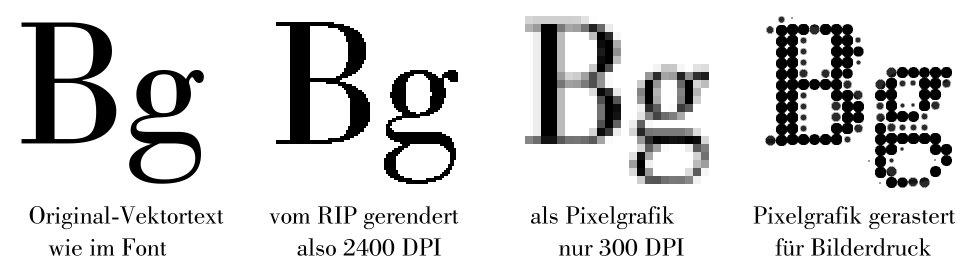
Um das Layout zu bearbeiten benutzen  Gimp (open Source)
Ich möchte da noch einmal dran erinnern. Wenn hier wirklich mit Texten gearbeitet werden soll, ist ein Pixel-Grafikprogramm die denkbar schlechteste Wahl. Textfunktionen von Gimp dienen ausschließlich dazu, in ein Foto mal ein paar Worte einzufügen, aber nicht, um damit ein ganzes Büchlein zu setzen.
Wenn es dann  wirklich ein OpenSource-Progamm sein soll, würde ich mir mal Scribus näher ansehen. Zwar noch immer meilenweit von Profrssionell entfernt, aber immerhin bleiben da Texte auch editierbare Texte, und eben nicht "Bilder von Texten" die man bei einem Schreibfehler komplett neu machen muss - zusammen mit dem Bild in das die dann eingebaut sind.
Notfalls lässt sich sogar Open/Libreoffice noch besser als Satzprogramm missbrauchen.
Wenn hier wirklich mit Texten gearbeitet werden soll, ist ein Pixel-Grafikprogramm die denkbar schlechteste Wahl. Textfunktionen von Gimp dienen ausschließlich dazu, in ein Foto mal ein paar Worte einzufügen, aber nicht, um damit ein ganzes Büchlein zu setzen.
Zum Vergleich: Es käme ja auch wohl niemand auf die Idee, einen Geschäftsbrief mit Wasserfarben und Pinsel zu malen, selbst wenn er keinen Computer hätte. Dann würde man wohl eher noch eine altmodische Schreibmaschine oder, wenn eine solche auch nicht zur Verfügung steht, einen Kugelschreiber benutzen.
… oder jemandem, der über entsprechende Gerätschaften verfügt, sagen: »Schreib mal bitte einen Brief für mich!«.
Ich will mal versuchen, das mit möglichst wenig Fachchinesisch zu erklären.
Es gibt 2 wesentliche Möglichkeiten, Grafiken im Computer zu speichern: Pixel und Vektoren.
Bei Pixeln - so wie sie Gimp verwendet - erzeugst du quasi ein Mosaik aus dem Bild, mit quadratischen Flächen, die jeweils eine bestimmte Farbe haben. Im Prinzip so ähnlich, wie diese "ministeck" Mosaik-Spiele (das waren ja im Grunde die ersten wirklich digitalen (von Digitus, dem Finger) Bildbearbeitungen)
Bei Vektoren dagegen wird nicht die Flache die mit Farbe gefüllt ist, beschrieben, sondern deren Außenkontur über mathematische Formeln, die abschnittsweise die Kurven beschreiben. Das innere dieses Vektor-Objekts kann dann mit einer Farbe gefüllt werden.
Computerschriften (Typ1, TrueType. OpenType sind im Wesentlichen eine Sammlung dieser Vektorgrafiken, ergänzt mit Anweisungen, wie diese dann als Text hintereinander zu reihen sind. Der Vorteil Vektorgrafiken kann man völlig frei beliebig vergrößern, ohne dass diese Mosaiksteinchen sichtbar werden.
Wenn du jetzt dein Bild drucken lassen möchtest, wird ja empfohlen, dass Pixelbilder hier eine Auflösung (bezogen auf die Druckgröße!) von 300 dpi haben sollen also in jeder Richtung 300 Pixel auf einen Zoll Druckbreite oder -Höhe, also auf 25,4mm.
Das bedeutet aber, das so ein Pixel dann knapp 1/10 mm hoch und breit ist.
Das geht dann für den Bildeindruck gut, weil bei Fotos und Zeichnungen, die gemalt sind die benachbarten Pixel sich zumeist nur wenig im Farbton und der Helligkeit unterscheiden.
Druckt man aber so einen Text, werden die Buchstaben eben auch auf diese 1/10 mm verpixelt, so dass im Falle, das die Vektor-Außenkontur beispielsweise genau auf der Hälfte so eines Pixels liegt, dieses komplett (bei schwarzer Schrift) in mittlerem Grau erscheint, und eine dünne Linie des Buchstabens, z.B. eine Serife oder eine Haarlinie färbt dann das Pixel vielleicht nur Hellgrau.
Da aber im Offset-Druck die Druckmaschine eben entweder nur komplett Farbe oder eben keine Farbe aufs Papier drucken kann, müssen Halbtöne dann auch noch gerastert werden.
Hat man aber ein Dokument, indem der Text auch tatsächlich noch Text ist, und zum ausgeben dann der Vektor-Font hinterlegt ist, wird der so genannte "Raster Image Prozessor" der Druckmaschine den Text auch in Pixel überführen, die dann auf die Druckplatte belichtet werden. Dies geschieht dann aber mit einer wesentlich höheren Auflösung mit Pixeln, die dann etwa nur noch 1/100 mm groß sind, und dann auch nicht in Halbtöne umgerechnet werden müssen. Hier ist dann das Pixel so lange weiß, bis es zu mindestens zur Hälfte vom Buchstaben überdeckt ist. Da wird der Buchstabe zwar auch etwas pixelig, die sind aber so klein, dass man die nicht sieht, und da dann auch keine Halbtöne im Spiel sind, wird da auch nicht noch einmal gerastert.
Ich habe das mal anhand einer stark vergrößerten Schriftdarstellung simuliert: